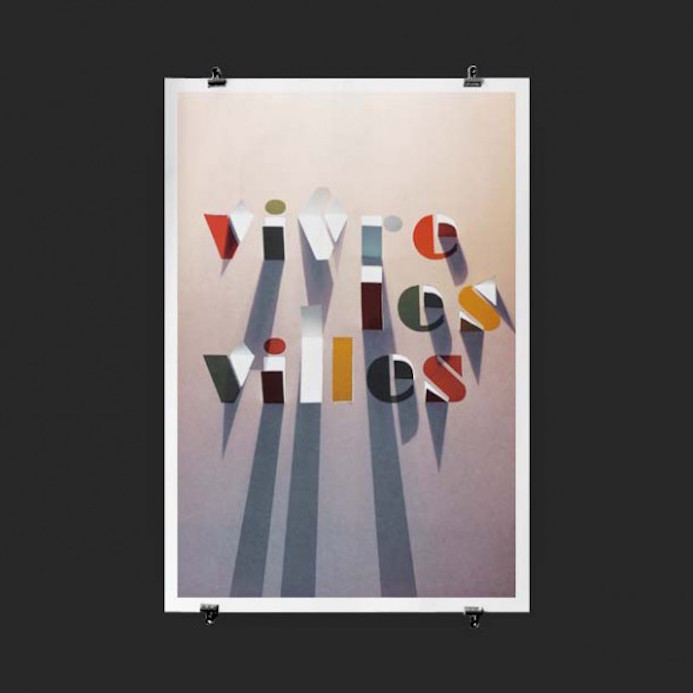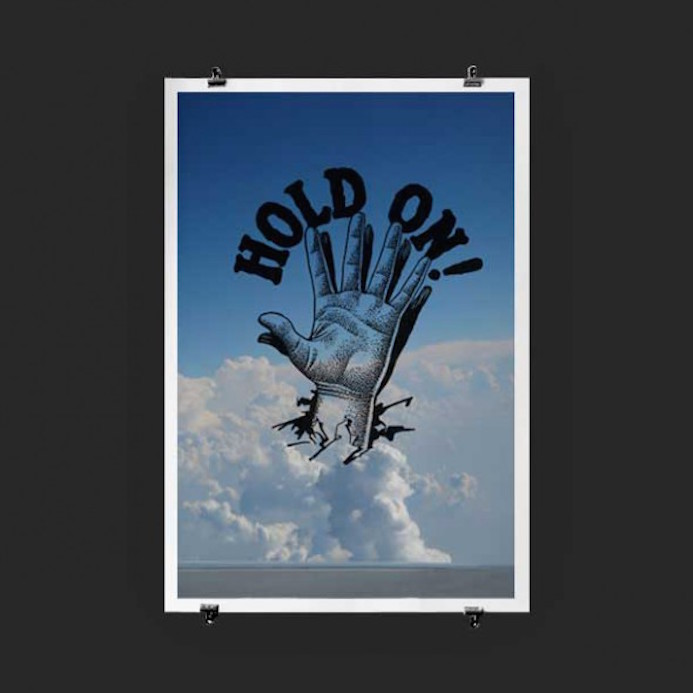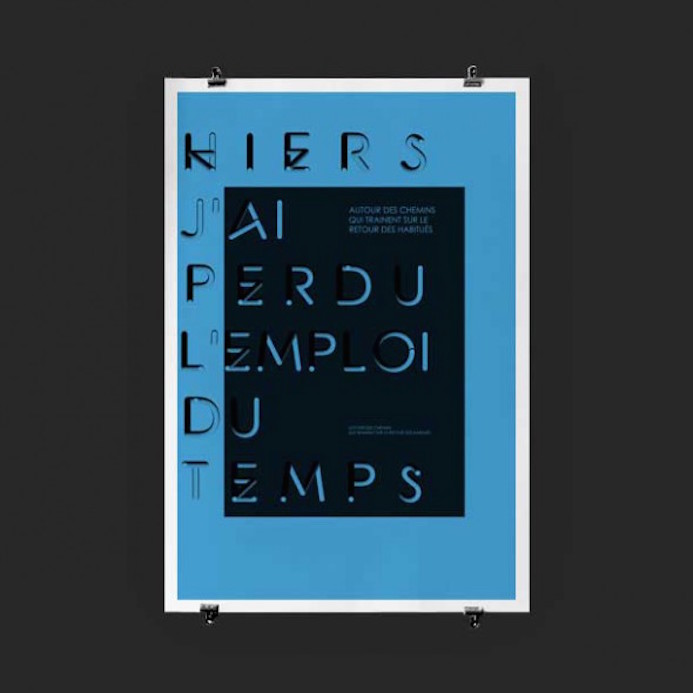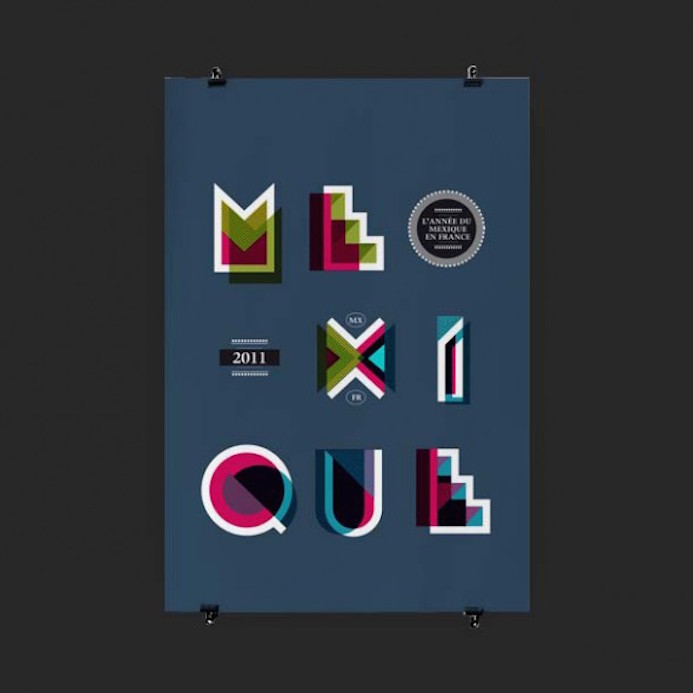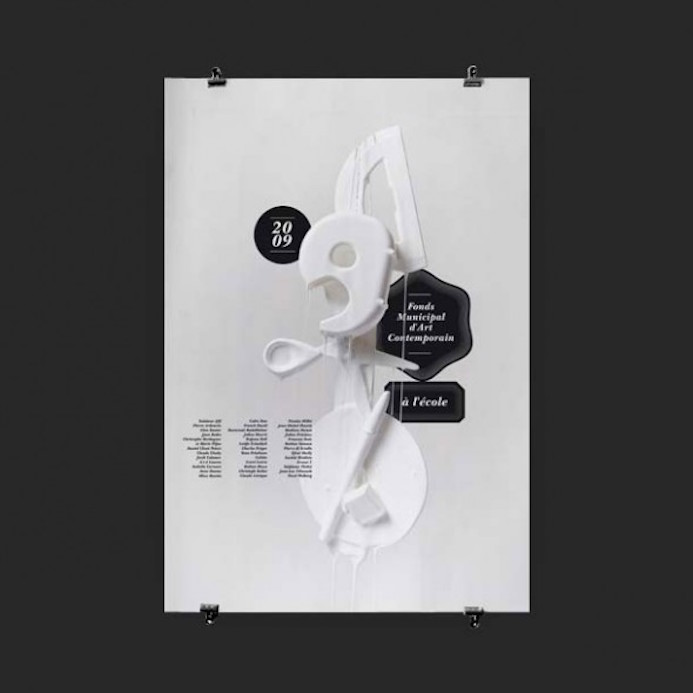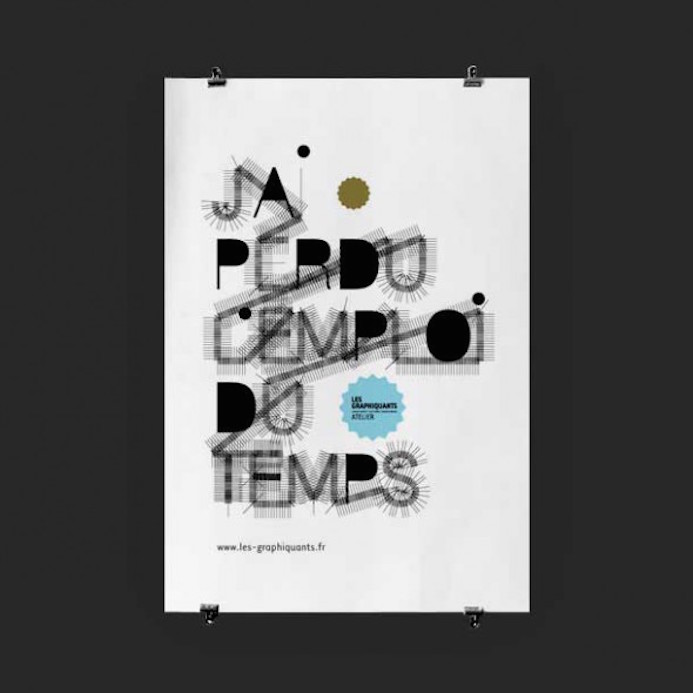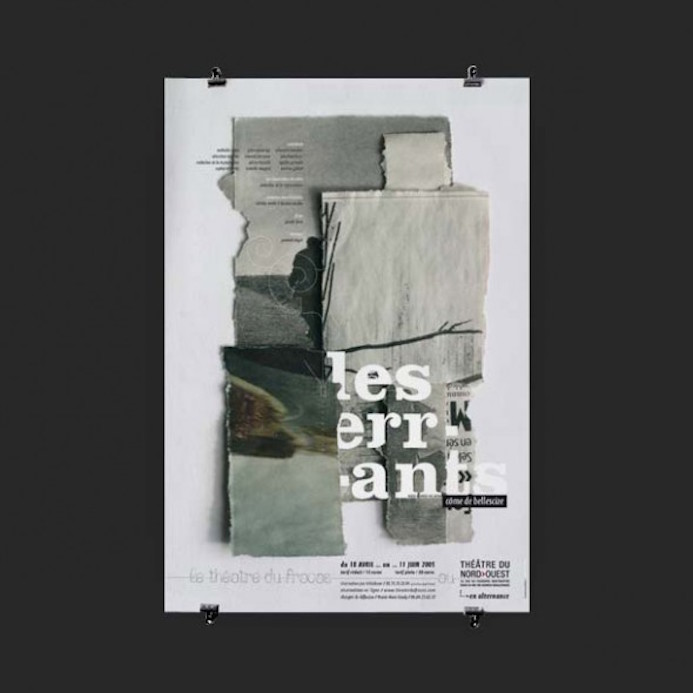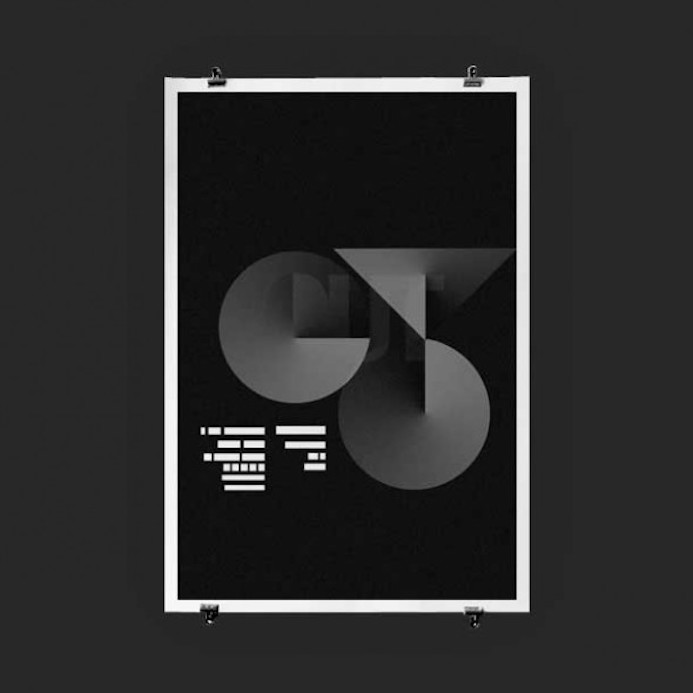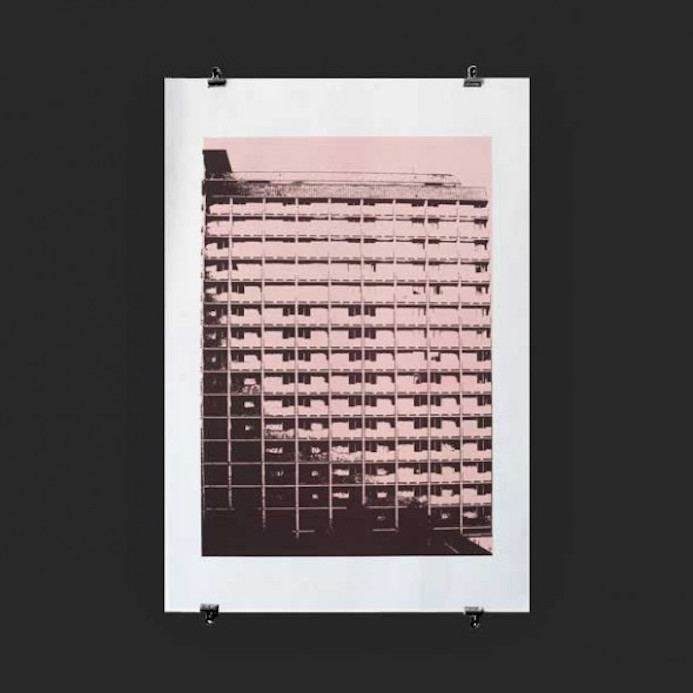
Cette semaine, c'est l'atelier de graphisme parisien Les Graphiquants qui nous inspire pour notre sélection de typographie hebdomadaire !
Ces affiches nous montrent différentes calligraphies et autres handlettering avec leurs propres mise en scènes !
Une belle collection d'affiches qui sublime la typographie dans tous ses états !